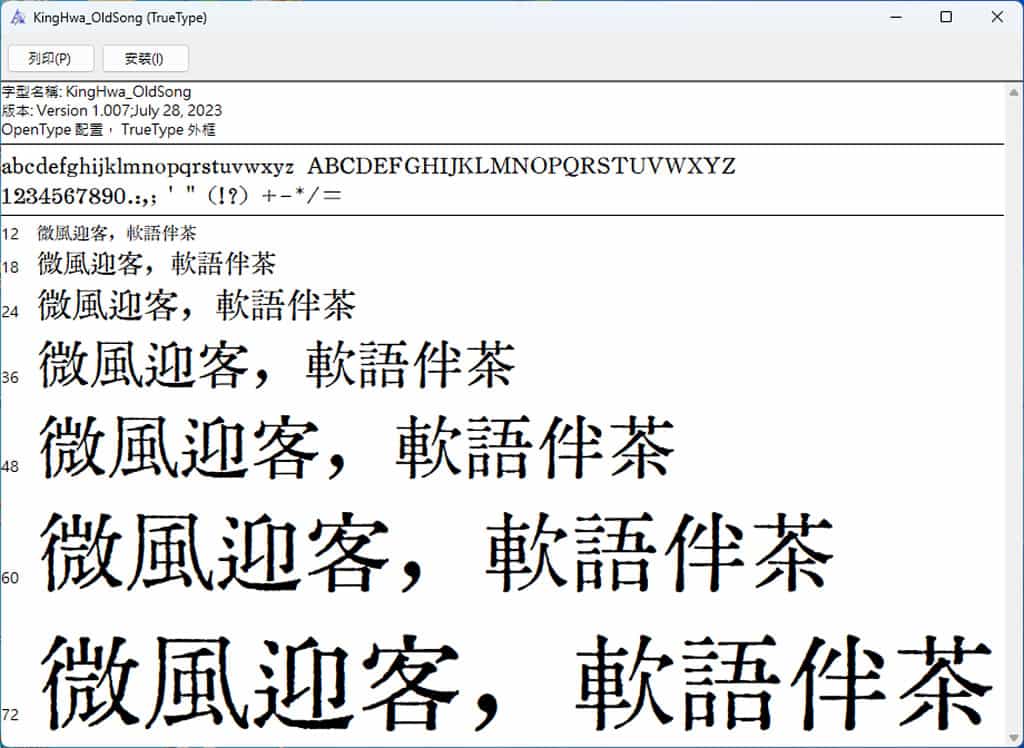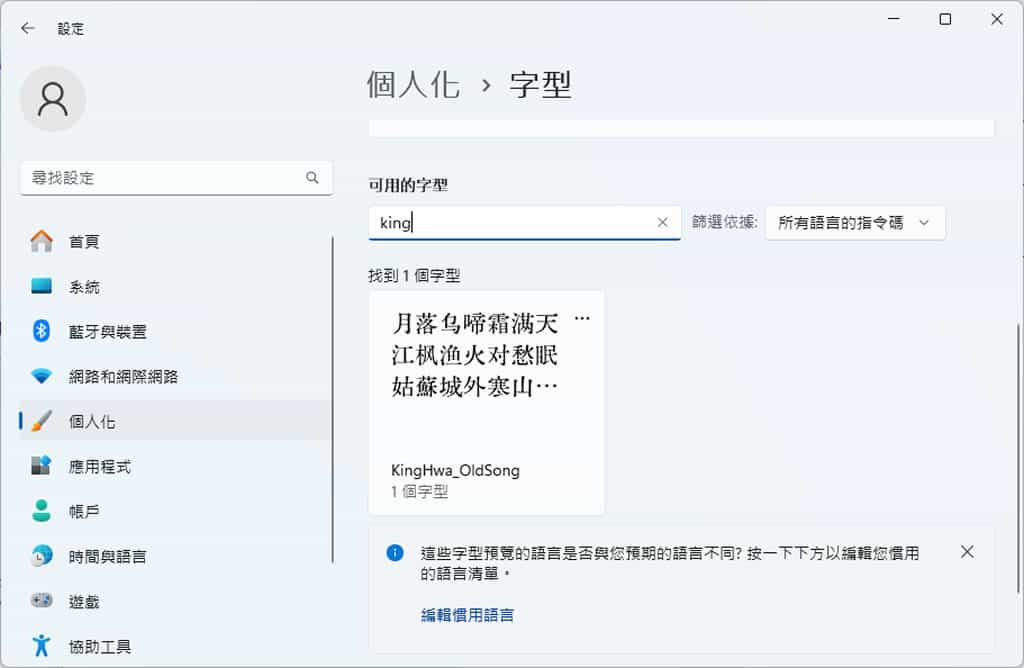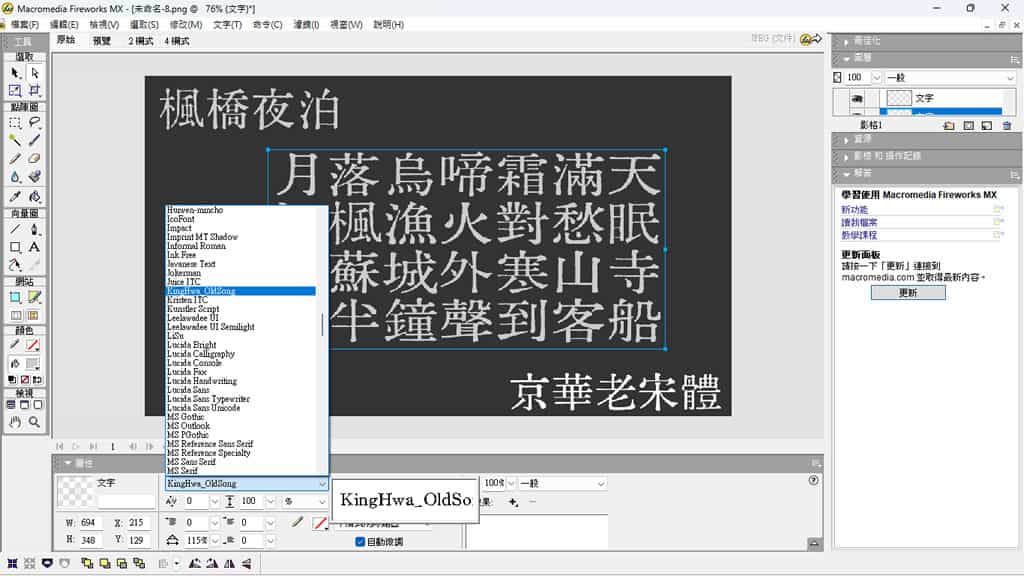
京華老宋體是由字體愛好者特里王發布的一套複古印刷字體。其風格源自 1961 年北京新華字模廠的 61-1 體,不僅印刷效果清爽,而且繁簡齊全,還提供新舊字體兩個版本。作者在舊書籍上發現這套字體後,透過掃描和 AI 技術將其還原並發布了京華老宋體。該字體具有桃形點、鵝頭勾和三角字肩的特點,極具仿鉛印字體風味,比現在常用的宋體更加厚重圓潤。此外,作者在授權聲明中特別強調,這套字體可免費商用,適用於各類平面、包裝、宣傳、影視、網頁等美術設計,也可嵌入電子產品、軟體應用之中,但不得單獨出售字體文件或用於違法活動。運用京華老宋體,可讓設計更添古典風情,不妨可以試試。
1.可至作者特里王發表該字體的官網上了解這套字體的背景故事,包括作者的啟發、字體尋找過程、掃描和最後借助人工智慧等一系列步驟,這個過程相當不容易。